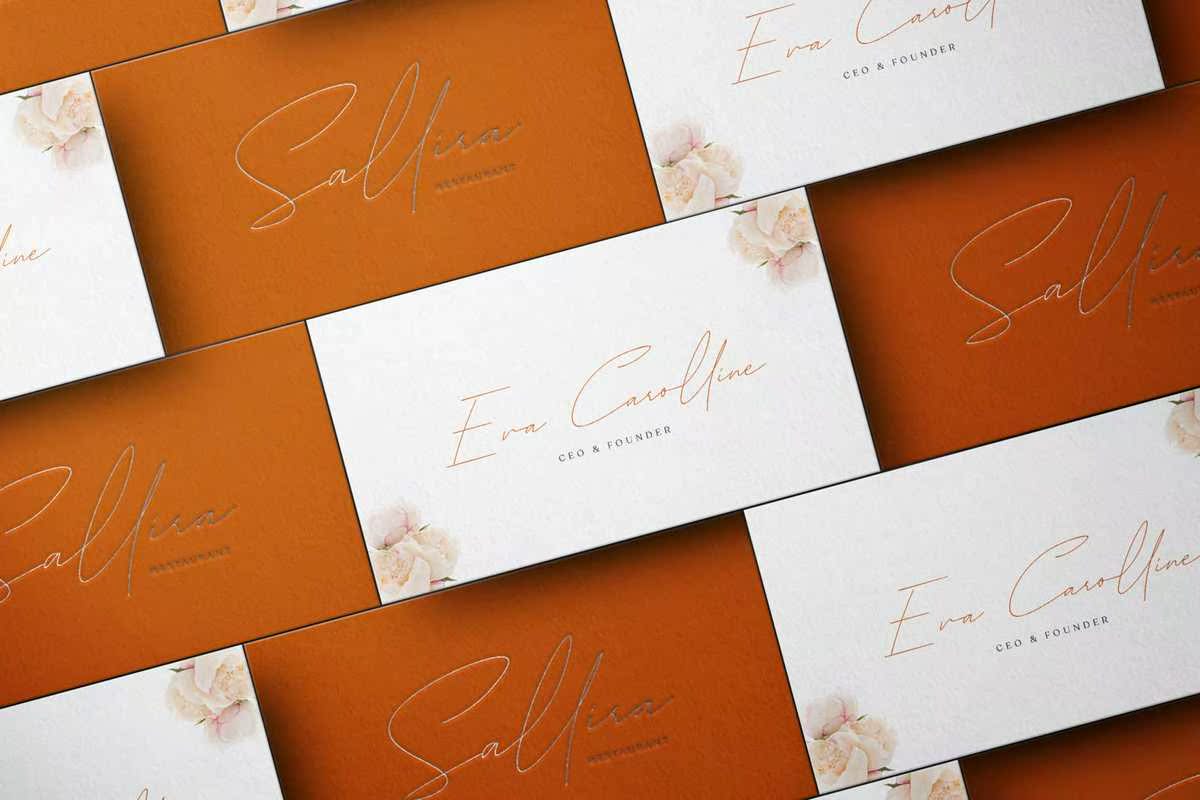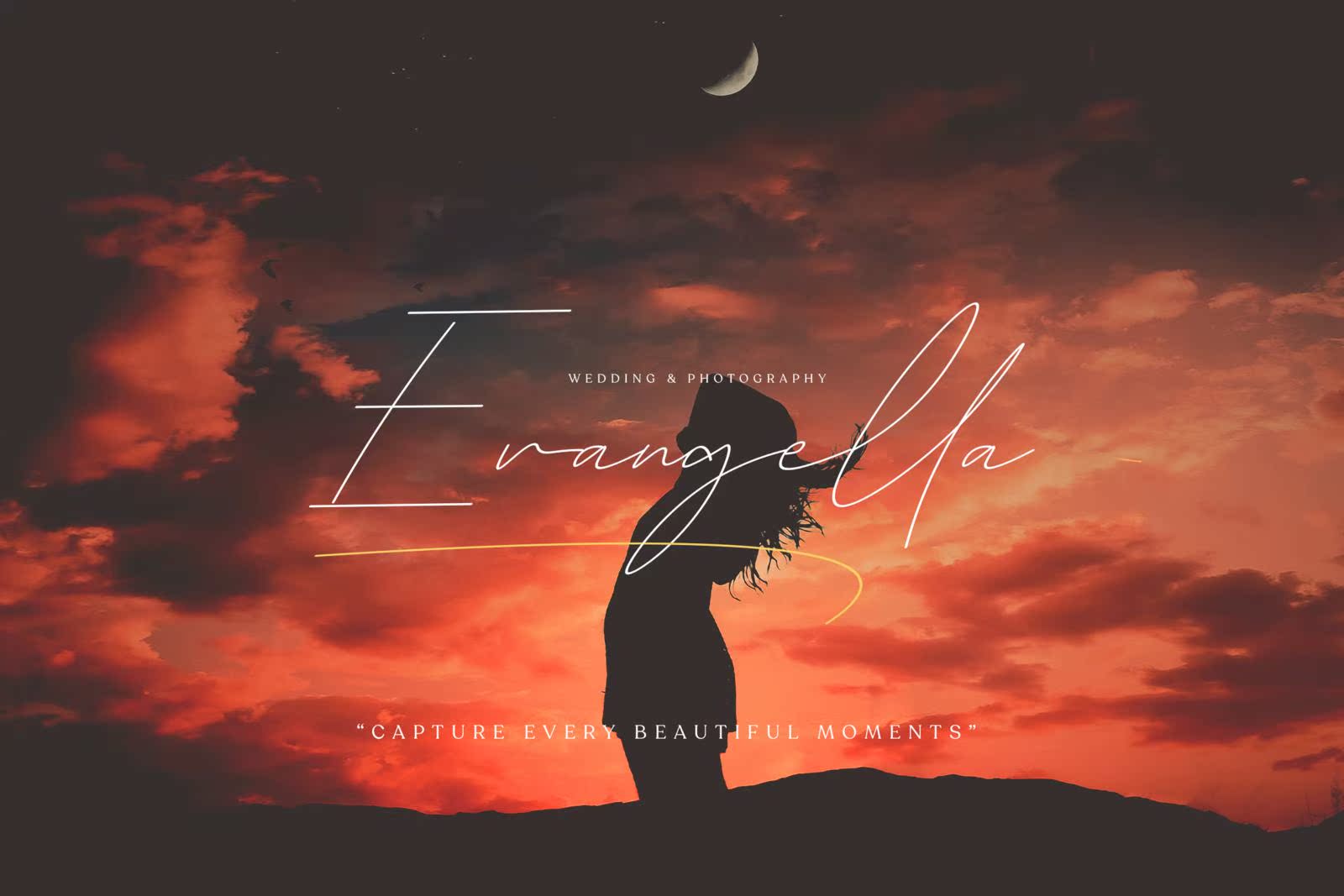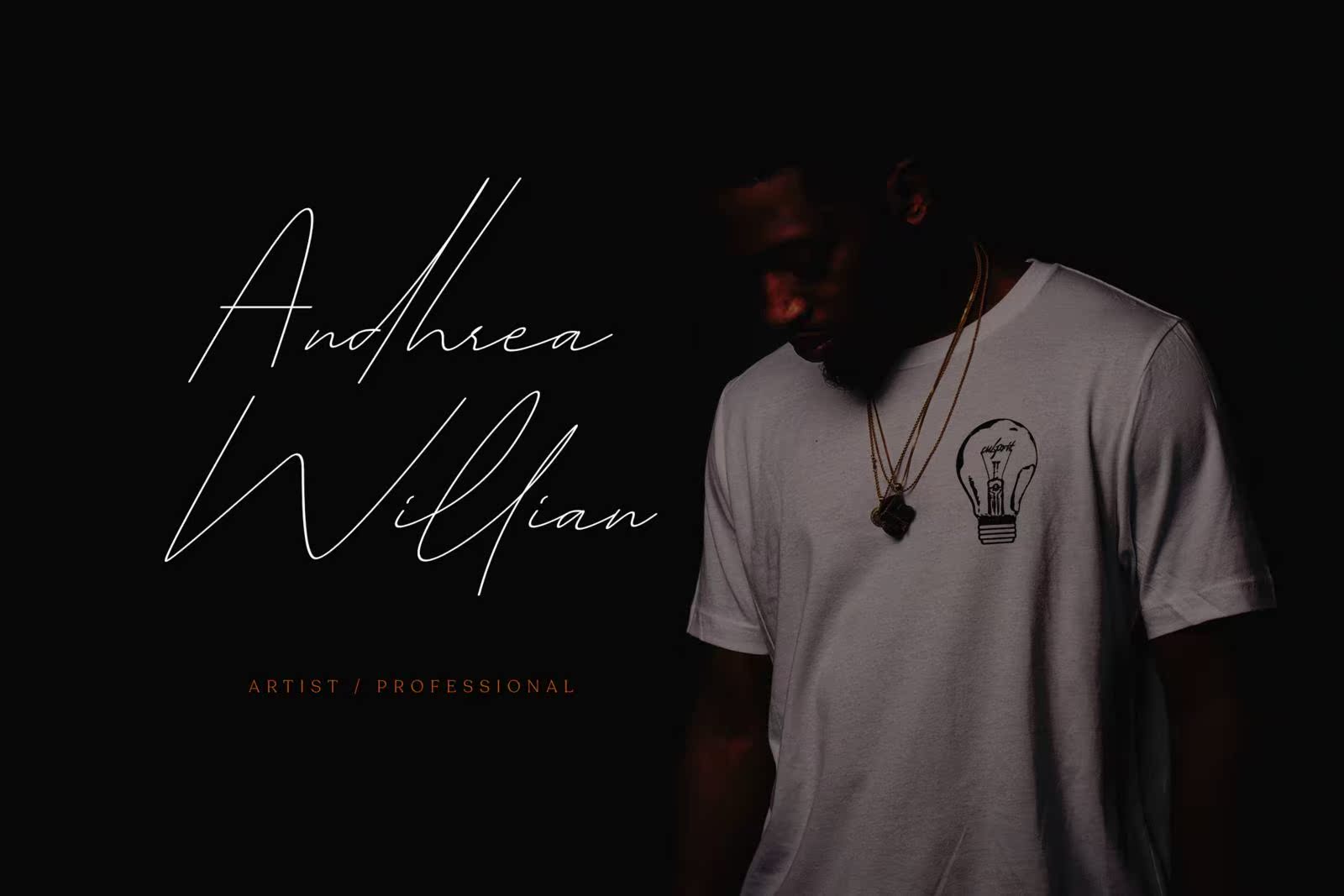
A具有Authentic样式的AssyHandWritenScriptFont。包括大写和小写字母、数字、标点符号、替换符号、连字、Swashand多语言支持。完美的Legant徽标、升级包装、婚礼统计、网站、,以及任何其他需要手写Uxurious Touch的项目。具有Authentic样式的Assy和WriteTenscript字体。包括大写和小写字母、数字、标点符号、替换符号、连字、Swashand多语言支持。完善Legent徽标、升级包装、婚礼统计、网站和任何其他需要手写Uxurious Touch的项目。